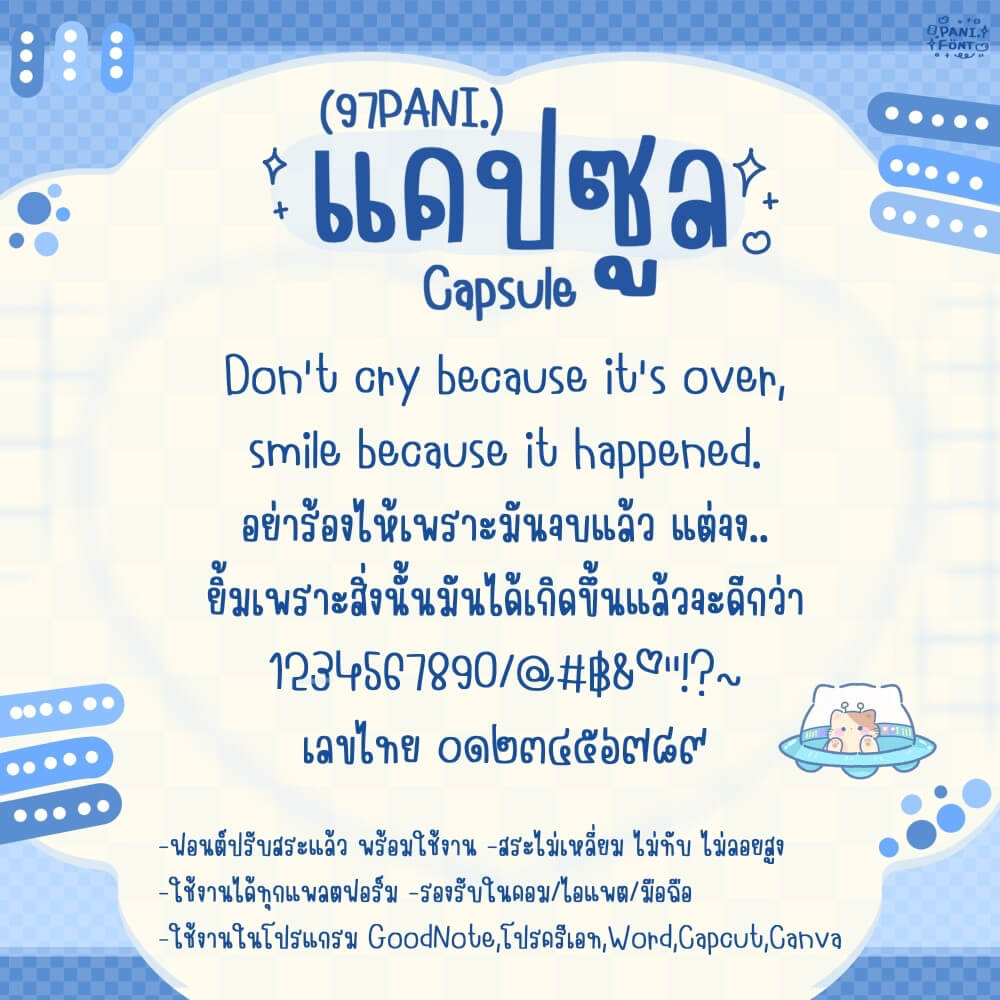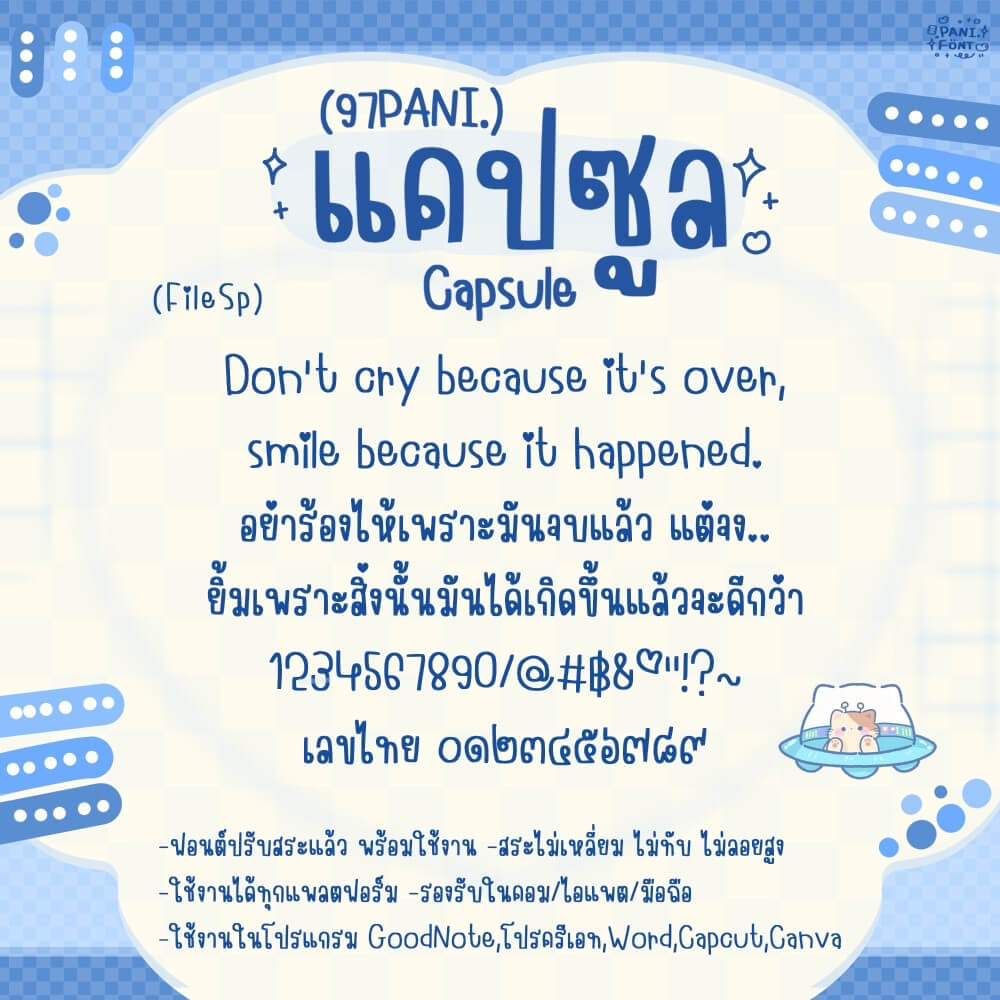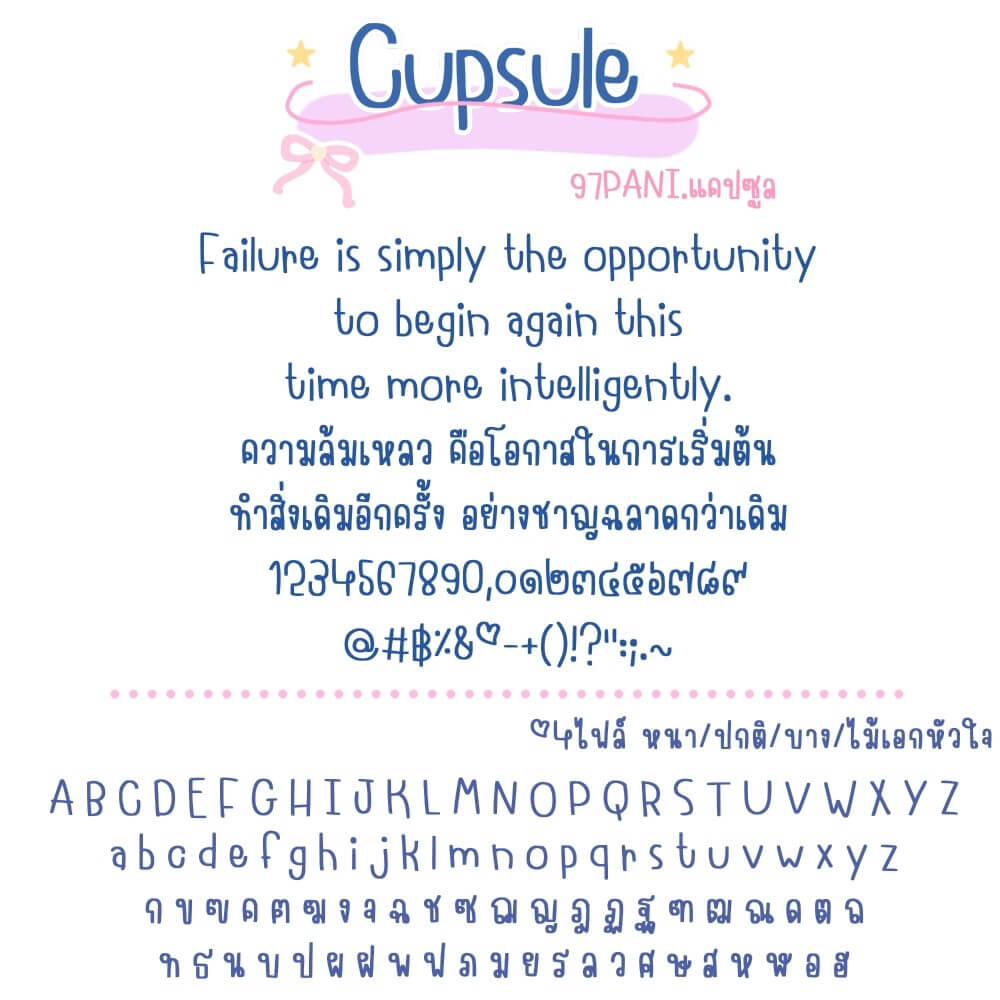
97PANI.แคปซูล
ฟอนต์ 97PANI.แคปซูล – ฟอนต์หัวกลม น่ารัก อ่านง่าย ใช้แต่งคลิป จดโน้ต ให้อารมณ์เข้าถึงง่าย
ฟอนต์มี 4 ไฟล์ – น้ำหนัก บาง ปกติ หนา ไม้เอกรูปหัวใจ